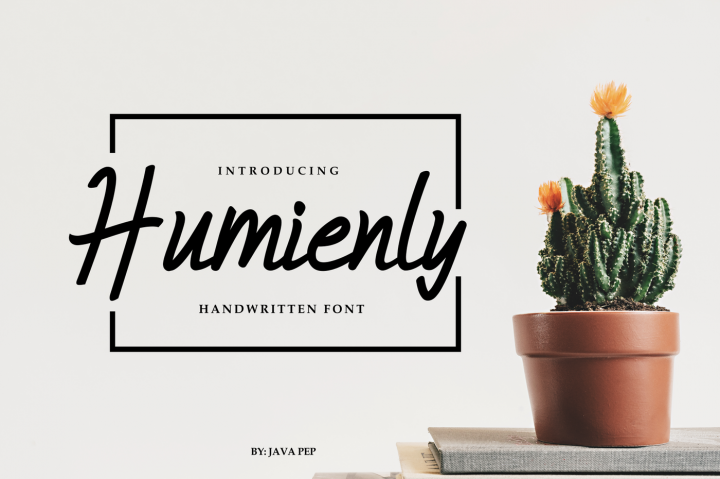
Humienly Script Font – Download Grátis
Descubra a delicada Huminly Script Font, uma fonte de script dedicada à simplicidade e elegância. Desenvolvida pelo designer Hamilton inspirado no termo “humano”, essa fonte transmite uma sensação amigável que se adequa aos mais diversos perfis. Através do seu traço autêntico, mas também feminino e masculino, a Huminly Script atinge um grau de versatilidade incomparável. Esta fonte é perfeitamente adaptável às diversas necessidades, oferecendo estilos modernos, clássicos, masculinos e femininos. A Huminly está à sua disposição para enriquecer suas criações, seja em portfólios de arte digital ou em projetos que exigem um toque humano nas letras.